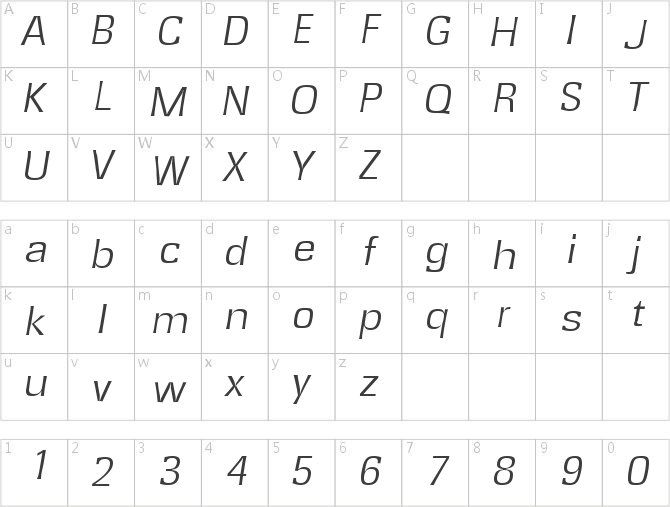
medwaylightsfitalic 詳情頁
medwaylightsfitalic字體字庫是一款讓人賞心悅目、百看不厭的英文字體,適合各類廣告和產(chǎn)品包裝設(shè)計(jì)應(yīng)用,字體大小0.05MB,格式為ttf字體,上傳用戶是W^xzj,作者/版權(quán)方為未知